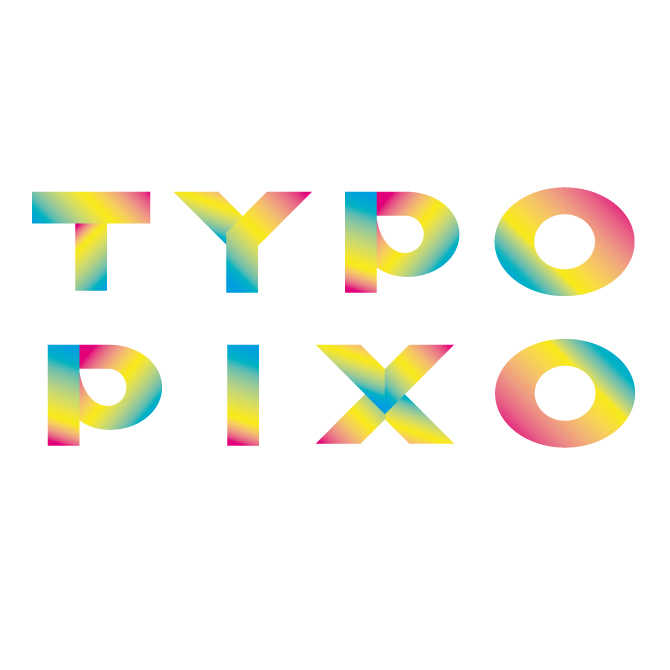
Farbige Webfonts sieht man bis dato noch recht selten. Das könnte sich nun langsam mit Typopixo ändern. Die in Amsterdam ansässige Foundry bietet eine feine Auswahl farbiger Webfonts.